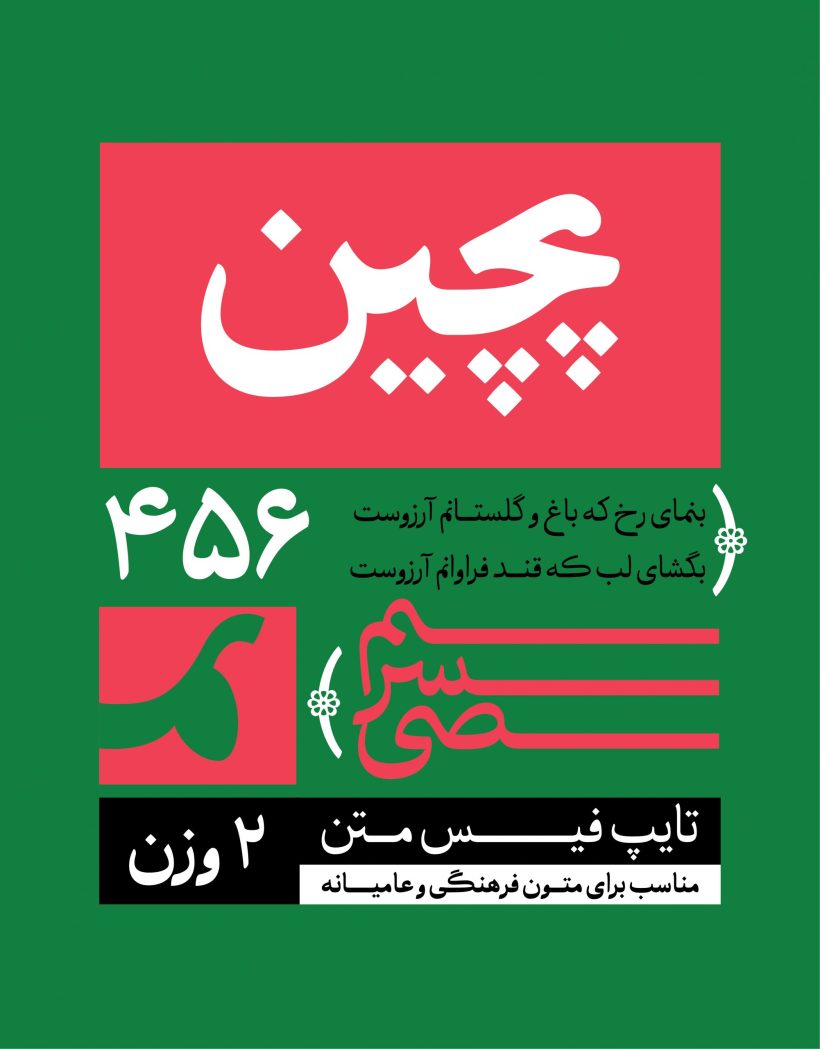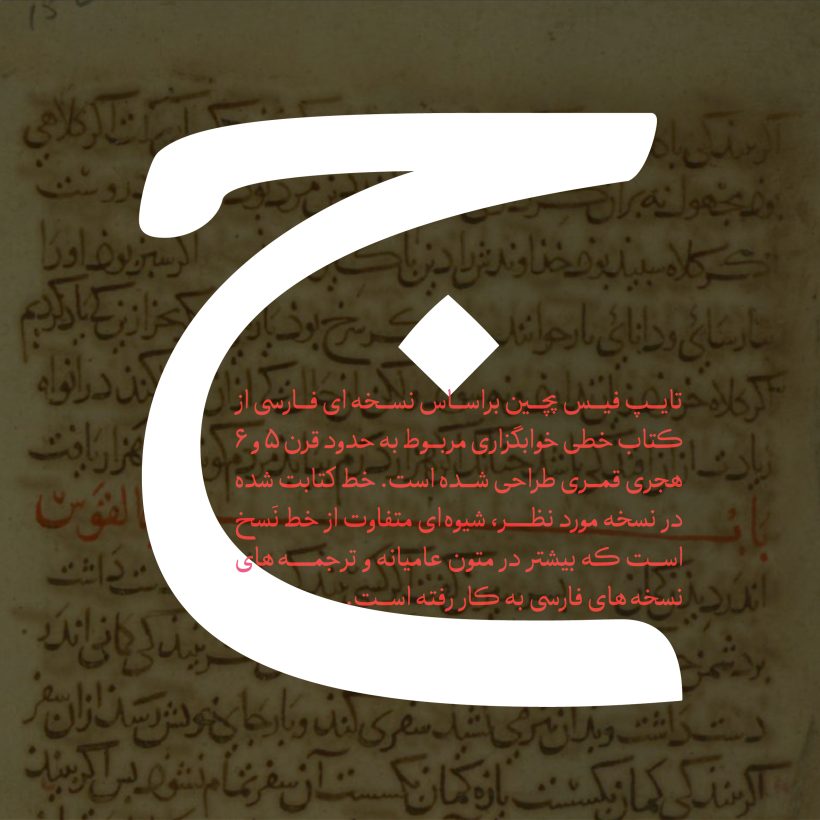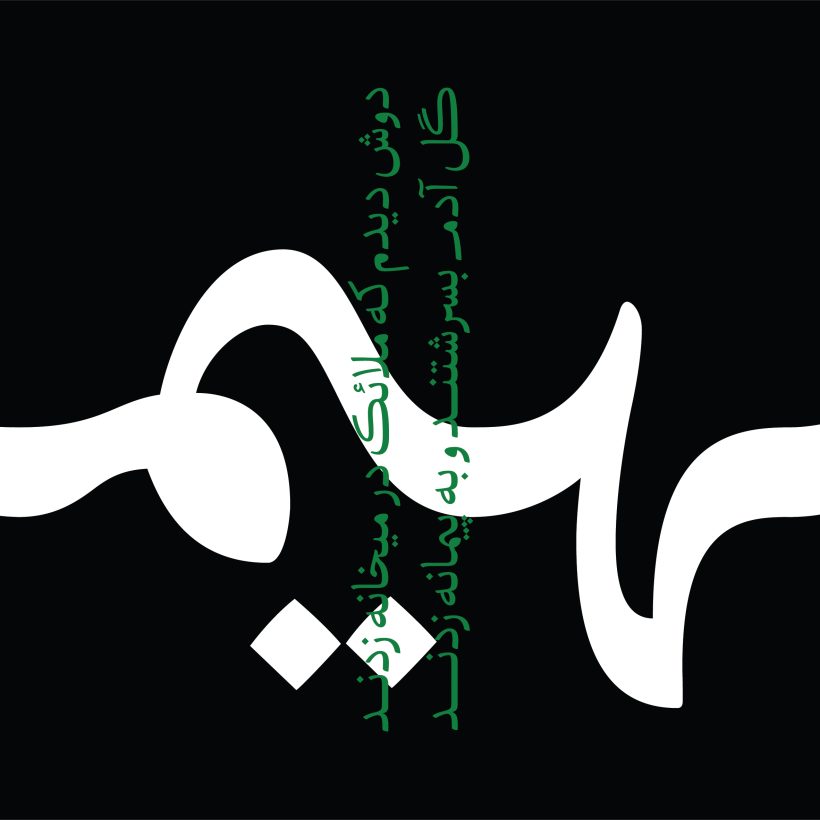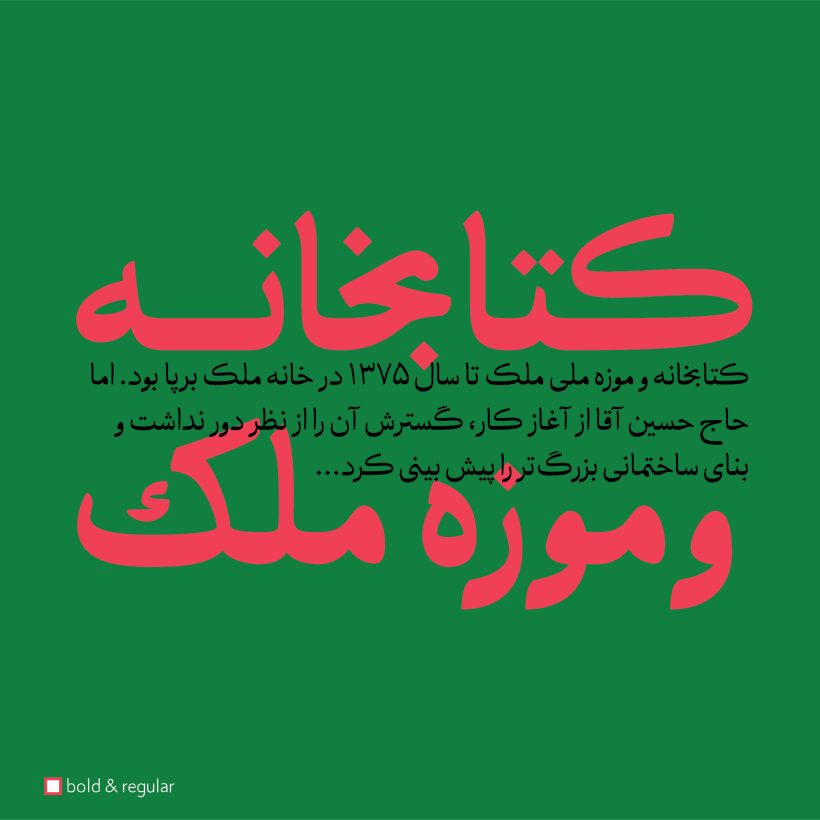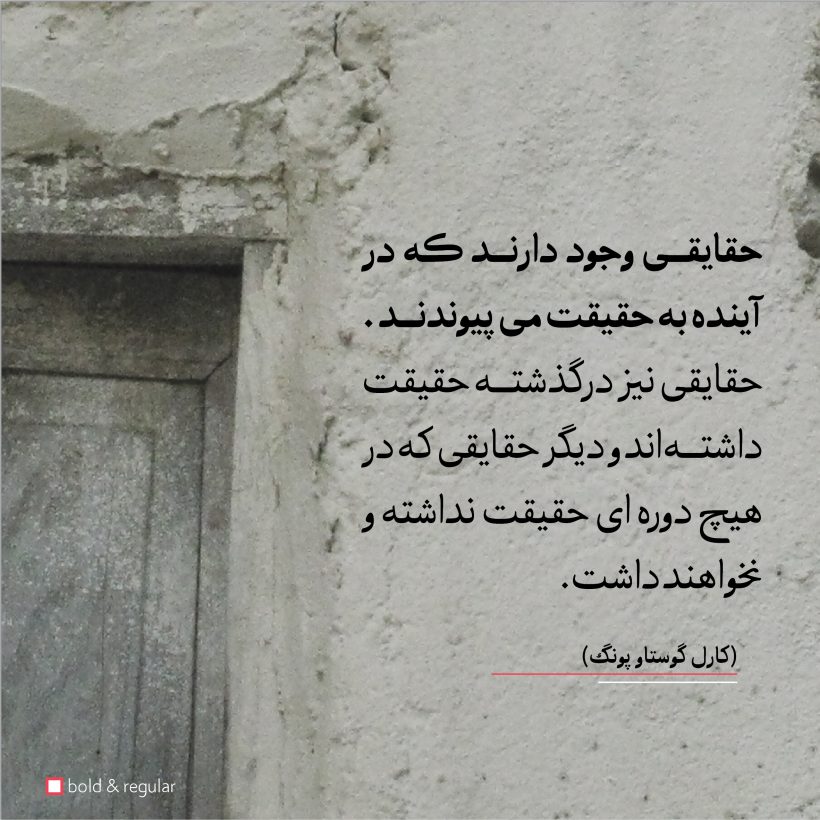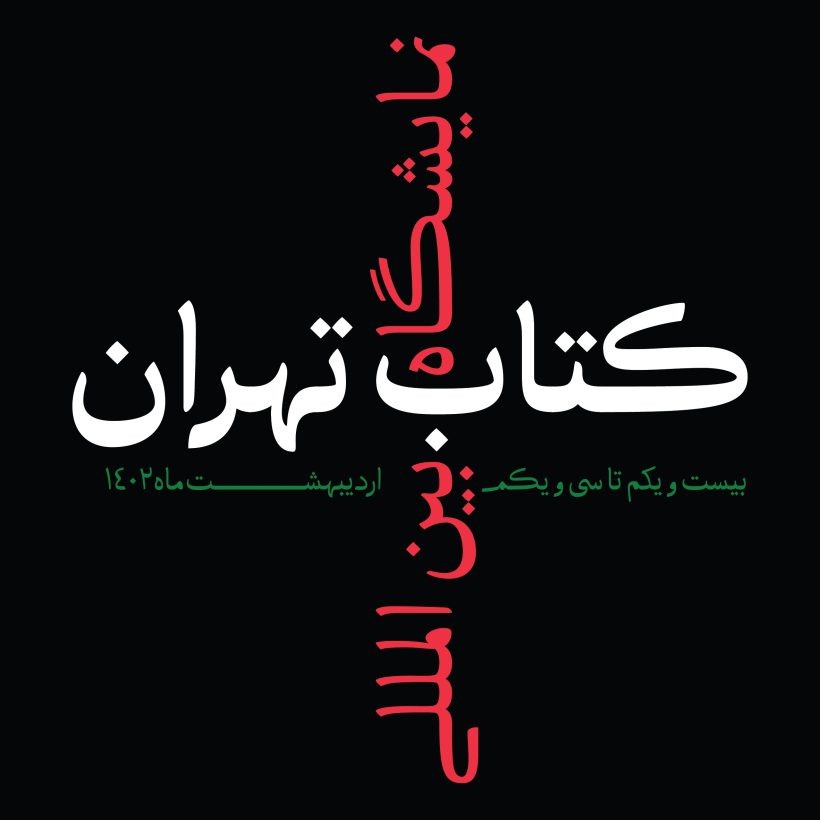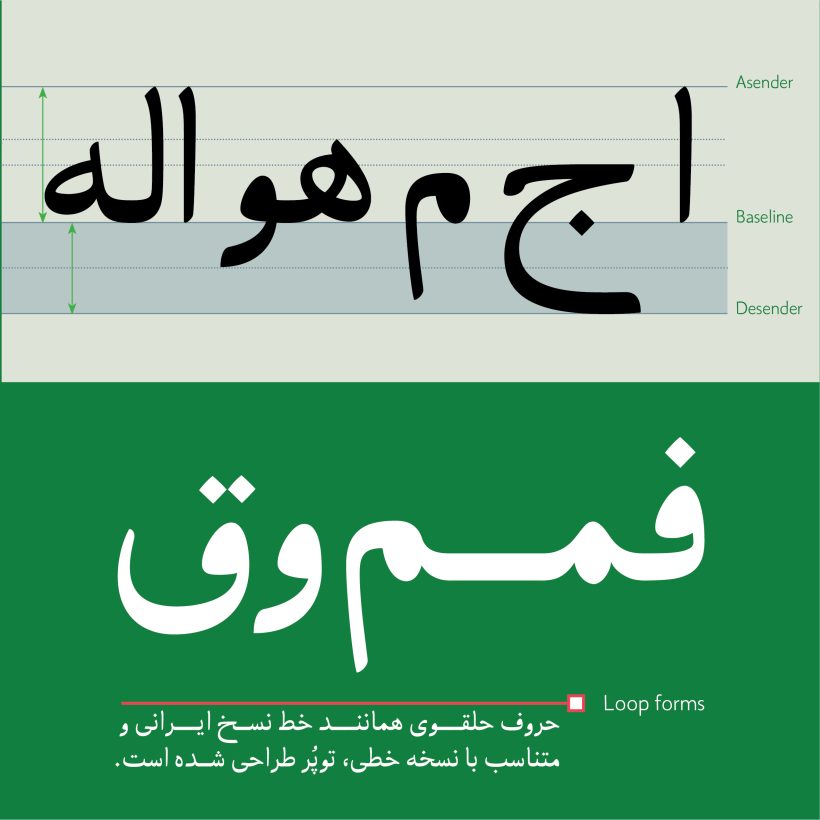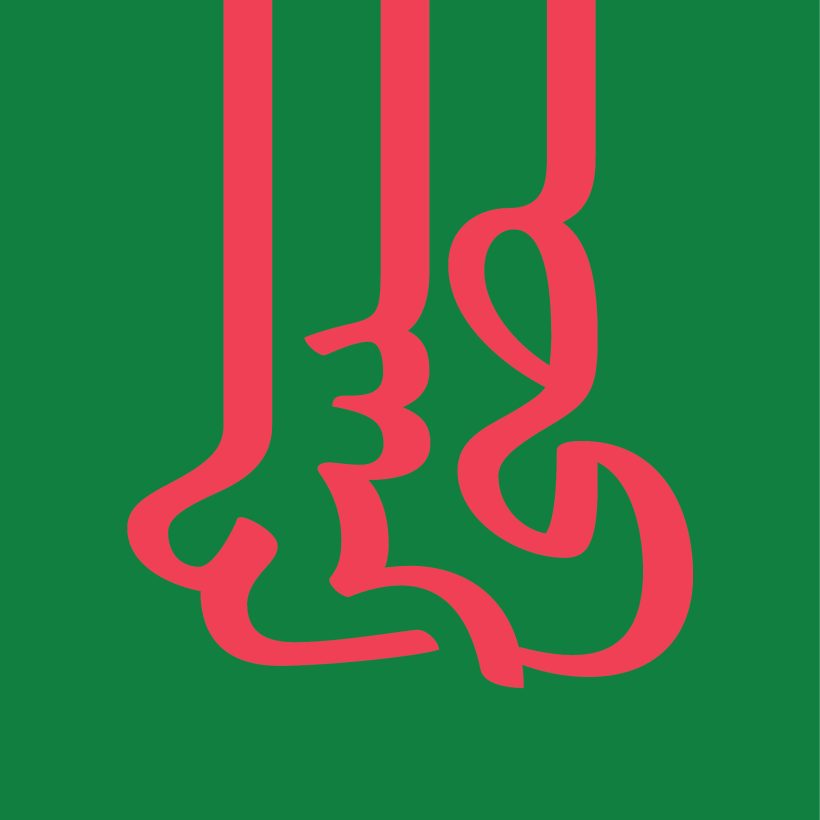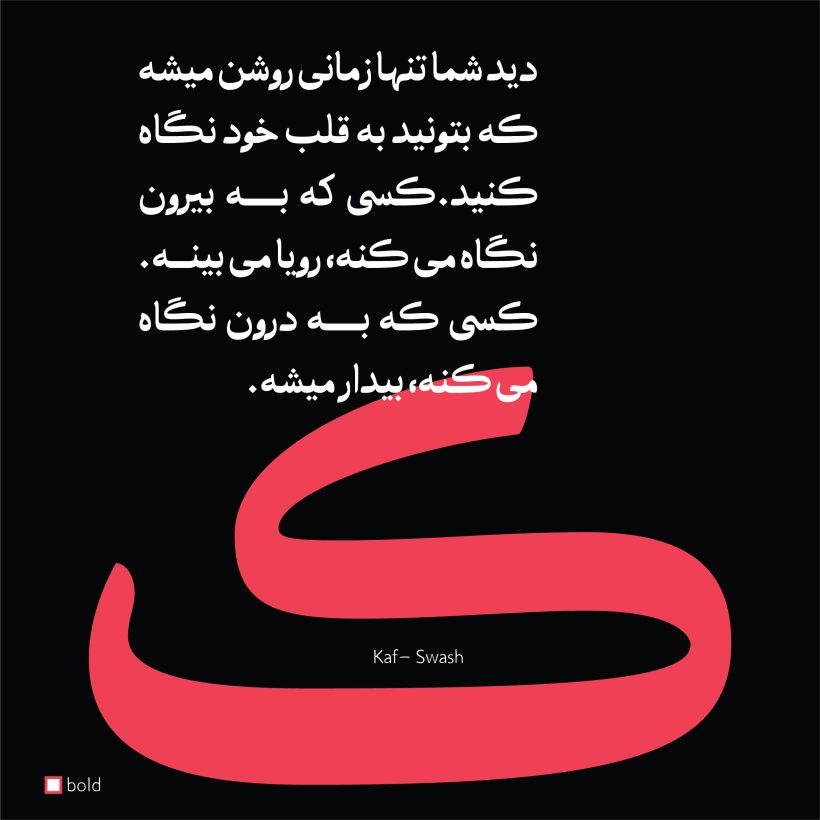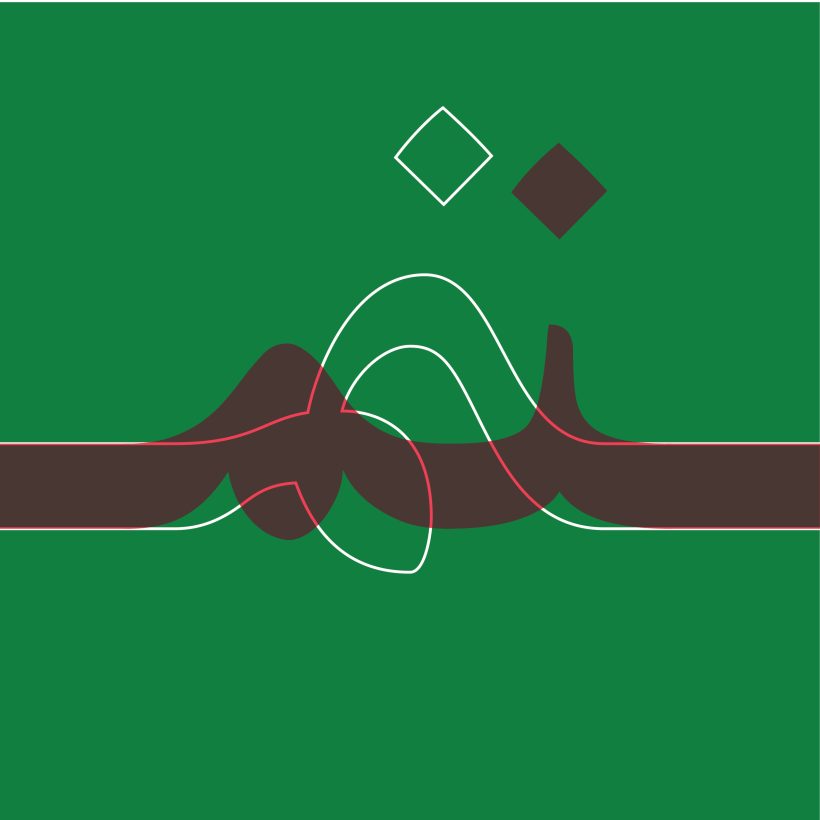
فونت پچین
تایپ فیس پچین براساس نسخه ای فارسی از کتاب خطی خوابگزاری محفوظ در کتابخانه مجلس شورای اسلامی مربوط به حدود قرن 5 و 6 هجری قمری طراحی شده است. خط کتابت شده در نسخه مورد نظر، خط نسخی است که بیشتر در متون عامیانه و ترجمه های فارسی به کار رفته و ویژگی های منحصر به فرد و کمتر دیده شده ای دارد و در فونت پچین نیز تلاش شده تا حد امکان ویژگی های فوق به کار گرفته شود. تایپ فیس پچین، لحن جدید و متفاوت را داراست و با توجه به ویژگی های فوق به نظر میرسد برای موضوعات فرهنگی و عامیانه مناسب تر باشد.
پچین شامل 2 وزن معمولی و بولد است. در فونت پچین متناسب با نسخه خوابگزاری ، از تعدد کرسی استفاده شده و الفات بلند قامت است و کرسی دوایر معکوس نیز به صورت عمیق طراحی شده است. حرکات سایر حروف حول کرسی وسط یا زمینه طراحی شده است. در فونت پچین برخی از حروف حلقوی مانند میم، واو، قاف و اشکال مشابه با روزنه های بسته طراحی شده است. قواعد کرنینگ و اعراب گذاری ها در فونت پچین اعمال شده است.
پچین دارای لیگیچرهای متنوع و پر کاربردی است که کارکترهای جایگزین محسوب می شوند و برحسب نیاز و برای زیبایی بیشتر قابل استفاده است.
اعداد فارسی و عربی در فونت پچین تنظیم شده و قابل استفاده است.